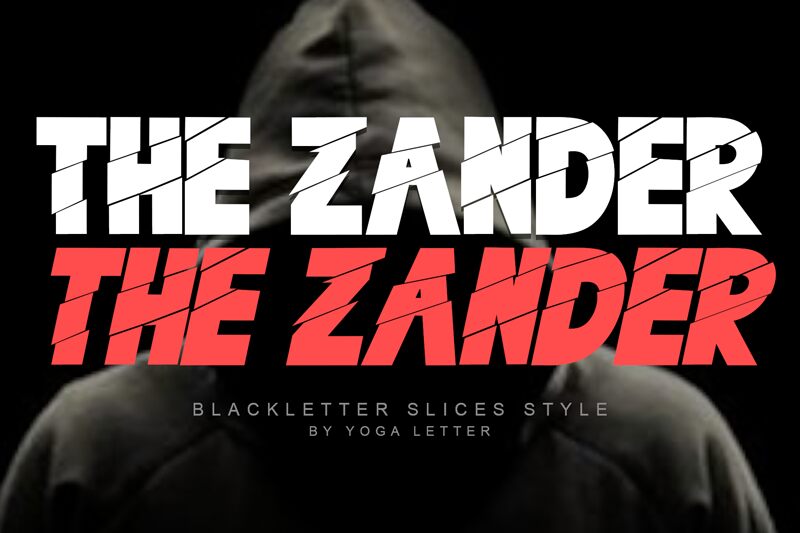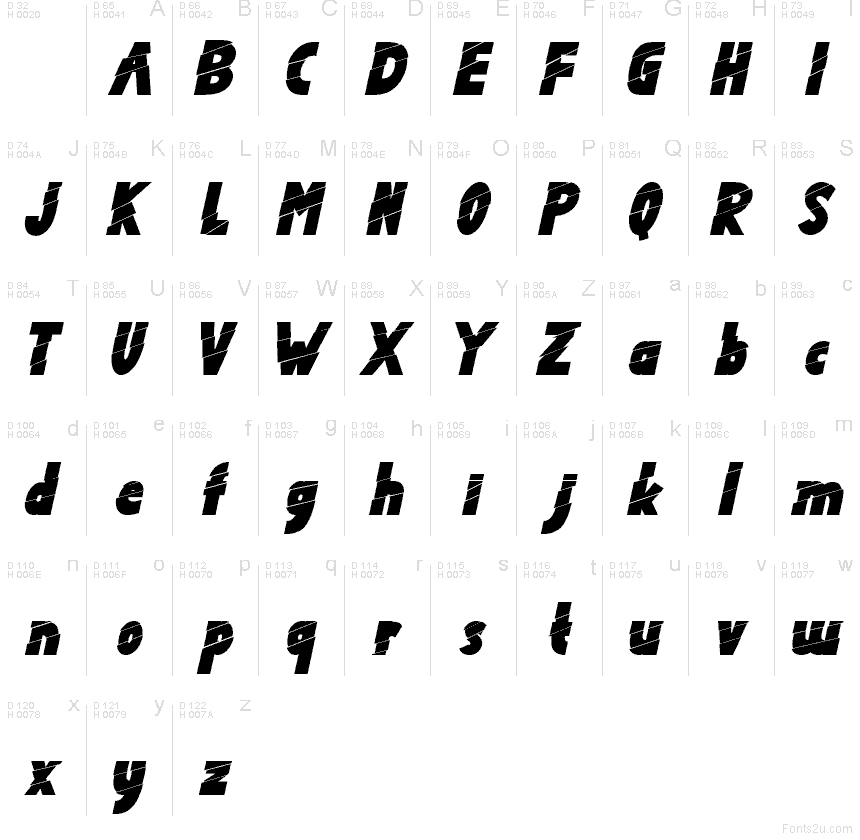
The Zander Demo Italic
The Zander Italic de Yoga Letter es una tipografía display gratuita y distorsionada que destaca por sus formas inclinadas, cortes transversales y roturas diagonales afiladas que interrumpen cada letra. Sus formas anchas y sólidas junto con sus cortes irregulares le confieren a la fuente un ritmo fragmentado y agresivo, sin perder nunca la estructura básica de los caracteres.
The Zander Italic funciona de maravilla en títulos de pósteres, gráficos de terror, portadas de álbumes, promociones deportivas y una imagen de marca atrevida que busque un toque incisivo. Esta fuente gratuita también es ideal para logotipos, diseños de merchandising y titulares breves donde los trazos rotos son capaces de sostener el diseño por sí solos.